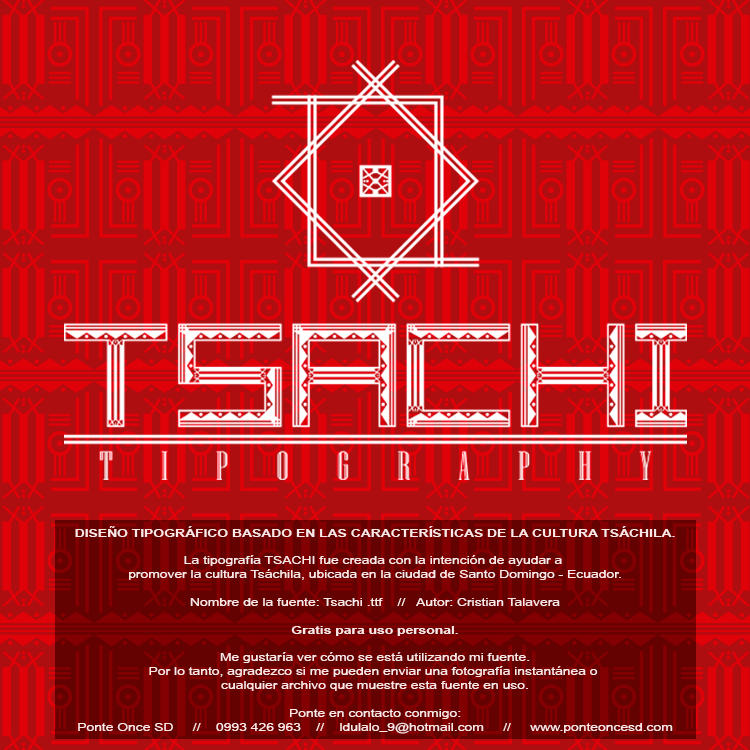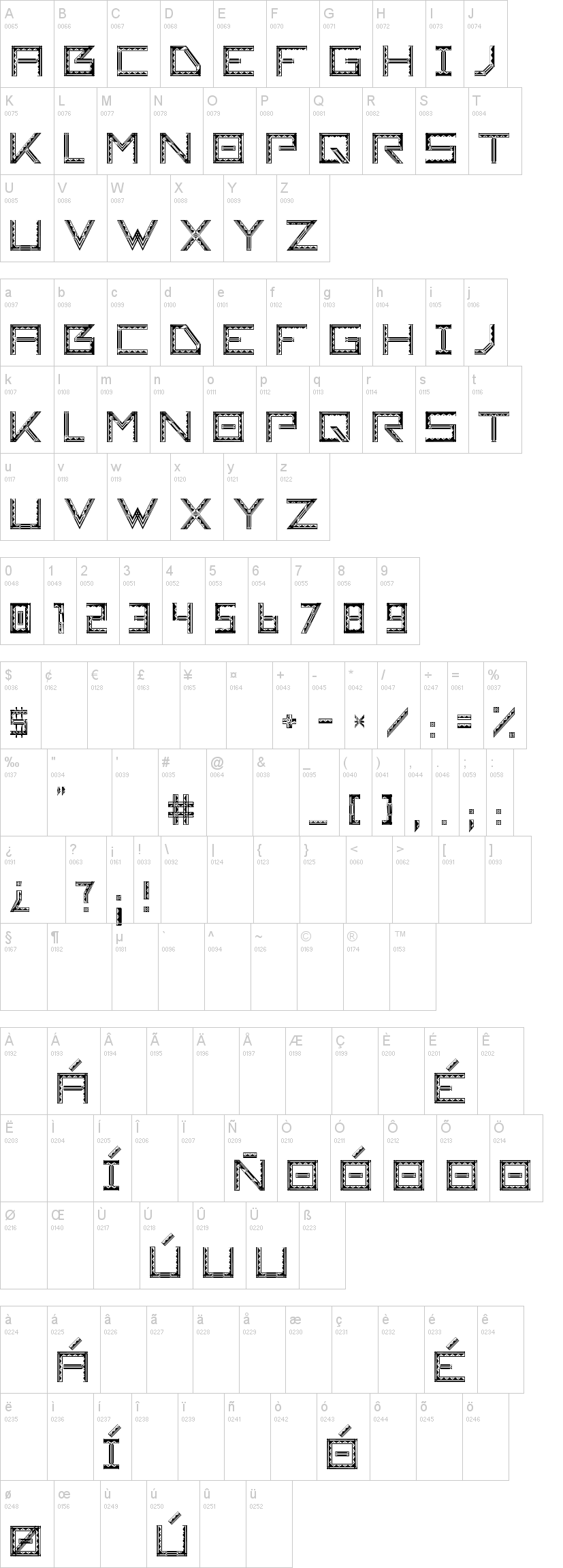
Note of the authorDISEÑO TIPOGRÁFICO BASADO EN LAS CARACTERÍSTICAS DE LA CULTURA TSÁCHILA.
La tipografía TSACHI fue creada con la intención de ayudar a promover la cultura Tsáchila, ubicada en la ciudad de Santo Domingo - Ecuador.